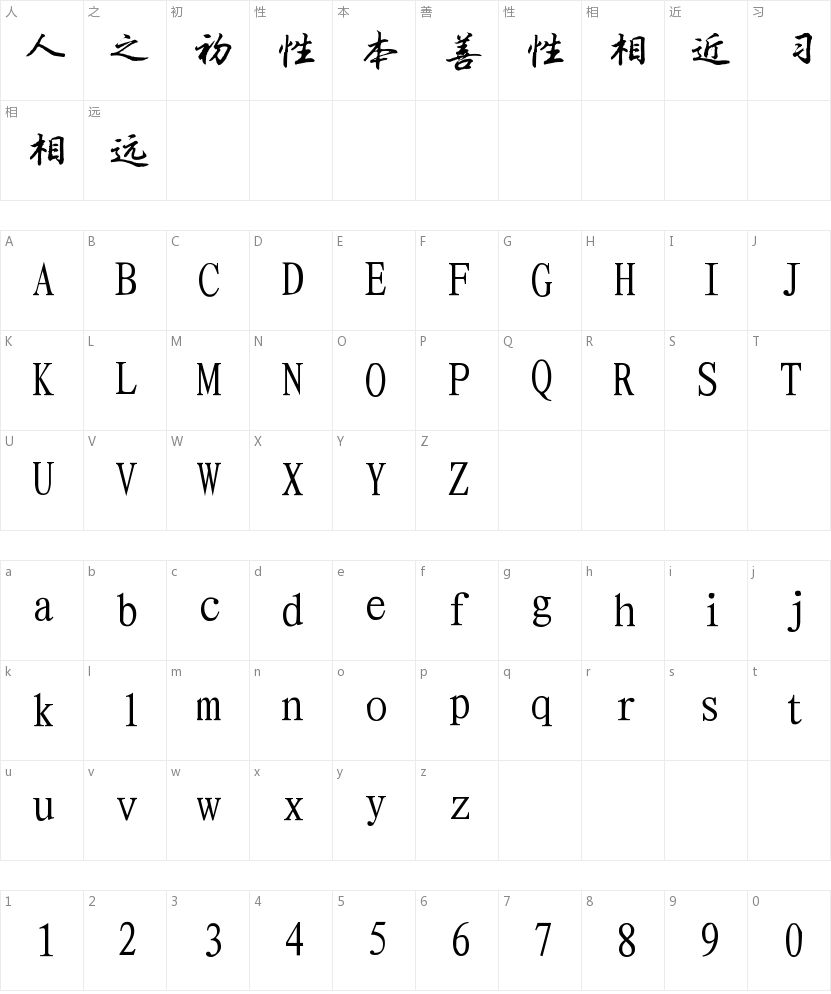
博洋行书3500
博洋行书3500是一款由博洋行书体设计研究所设计的中文字体,它具有清新、简洁大方的风格,字形笔画流畅,曲线优美,符合中国传统文化的美学特点,是一款适用于各种文字编辑、印刷、网络及多媒体等应用的中文字体。它有着规范的字形结构,拥有更高的识别率和可读性,使用者可以更加轻松地掌握文字内容,从而提高文字的视觉效果。
博洋行书3500是一款非常不错的手写艺术字体,具有很好的视觉感,适合于文化类的宣传设计、商业类品牌的广告和产品包装设计以及个性化文字排版等较多场景。